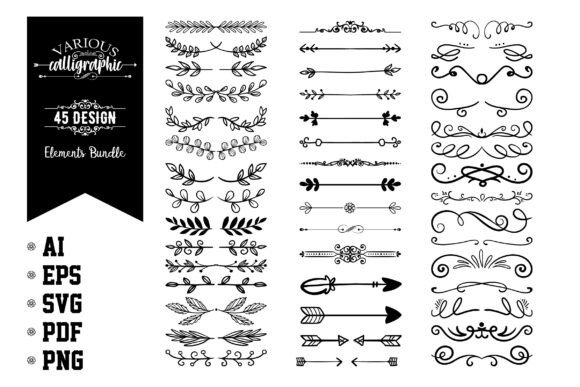
Various Calligraphic Design Elements Set
การค้นหาองค์ประกอบการออกแบบที่เหมาะสมอาจเป็นเรื่องท้าทาย แต่ Various Calligraphic Design Elements Set นำเสนอคอลเลกชันที่โดดเด่นซึ่งช่วยยกระดับงานของคุณได้ทันที
สร้างขึ้นอย่างแม่นยำ Various Calligraphic Design Elements Set ให้เวกเตอร์ที่สะอาด พิมพ์ตัวอักษรที่ราบรื่น และใบอนุญาตเชิงพาณิชย์เพื่อความสบายใจ
ไม่ว่าคุณจะสร้างผลิตภัณฑ์ POD (Print on Demand) คำเชิญงานแต่งงาน หรือกราฟิกโซเชียลมีเดีย Various Calligraphic Design Elements Set ก็เหมาะสมอย่างยิ่ง